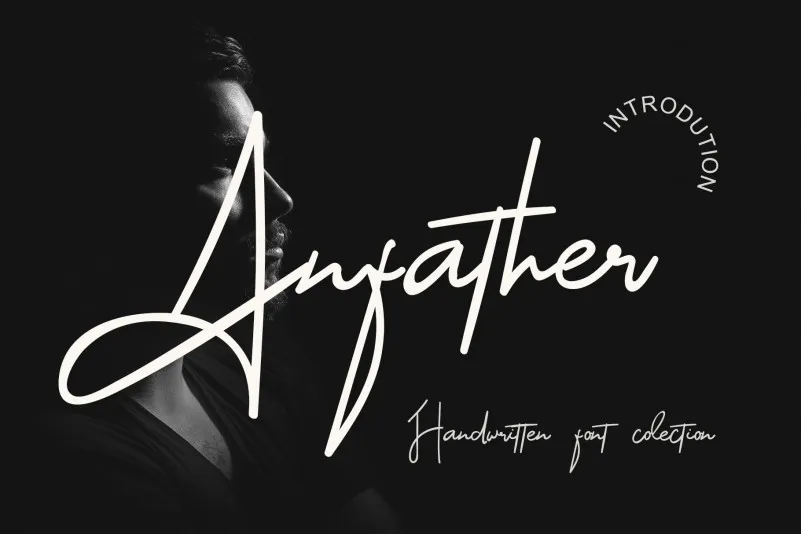
Anfather Font é uma elegante fonte escrita a mão que certamente enriquecerá seu próximo projeto visual. Ideal tanto para criar logos memoráveis quanto para estilos de branding e frases inspiradoras, esta fonte oferece um toque único e bonito em cada letra, iluminando suas criações com vida. Ela é uma escolha excepcional para aqueles que buscam uma mão-de-obra artística que complementará qualquer projeto visual sem parecer forçada ou desajustada. Inspiradora e versátil, Anfather Font oferece uma perspectiva única à sua identidade visual, seja ela no design de logomarcas, em um projeto editorial ou até mesmo como parte de citações memoráveis. Com seu designer talentoso kateengciu, você pode confiar que cada característica do seu design será cuidadosamente pensada e personalizada para maximizar a presença visual e o impacto emocional do texto.